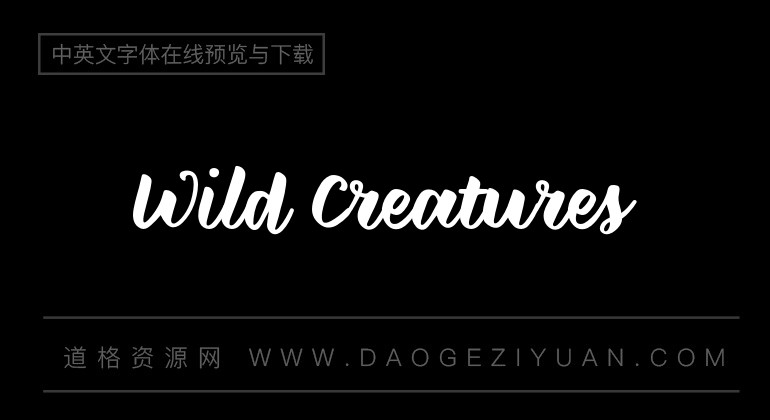
Wild Creatures
Wild Creatures 是一种手写风格的字体,具有野性、自然的感觉。这种字体的特点是字形不规则,线条粗细不均匀,形状像是用笔刷画出来的,让人感觉有一种原始的、朴实的感觉。它适合用于户外、冒险、野外等主题的设计,如旅游、休闲、户外运动等方面。使用 Wild Creatures 字体能够为设计作品增添一种粗犷、自然、野性的气息,非常适合创意设计、平面设计、海报设计、广告设计、产品包装等领域的应用。
Wild Creatures是一款非常不错的手写艺术字体,具有很好的视觉感,适合于文化类的宣传设计、商业类品牌的广告和产品包装设计以及个性化文字排版等较多场景。